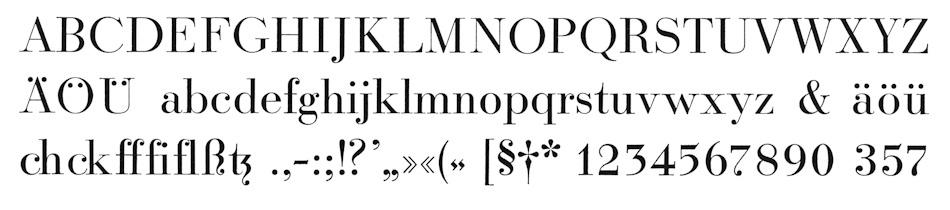
Schriftart eines 50er Jahre Kunstbuch gesucht
Ich besitze aus dem Bestand meiner Mutter das Buch I. Schlosser "Das alte Glas" von Klinkhardt & Biermann, Brauschweig.
Ich hab schon bei den Font-Suchmaschinen geschaut, die ähnlichste ist Ratio Modern, allerdings fehlen bei diesem Font oft die Kehlungen, sowie die in die Versalhöhe herein gezogenen Umlautpunkte. Daher denke ich, eine saubere Digitalisierung könnte sich lohnen. Daher meine Frage, wie heißt die originale Bleisatz-Schrift?